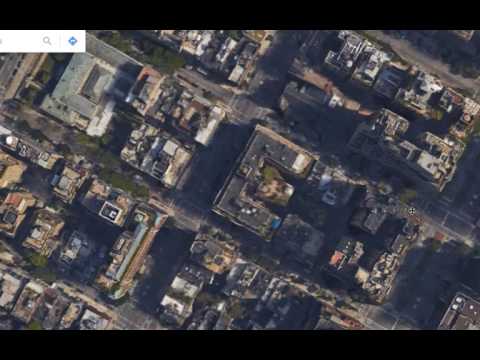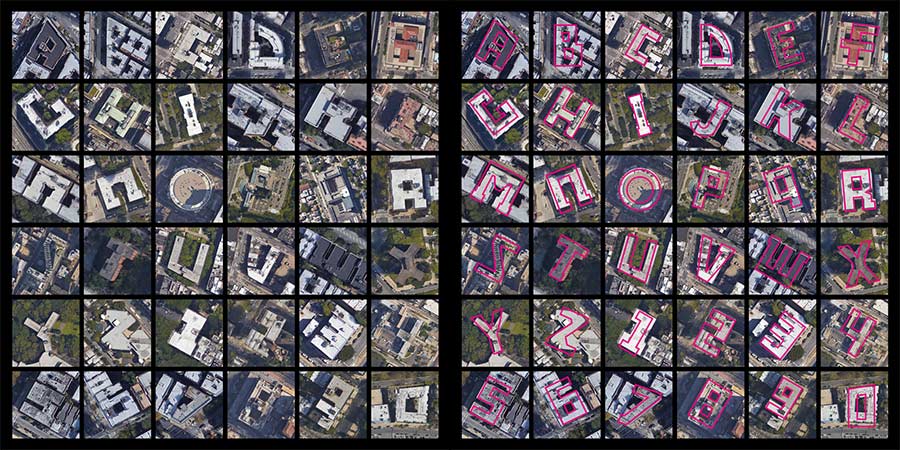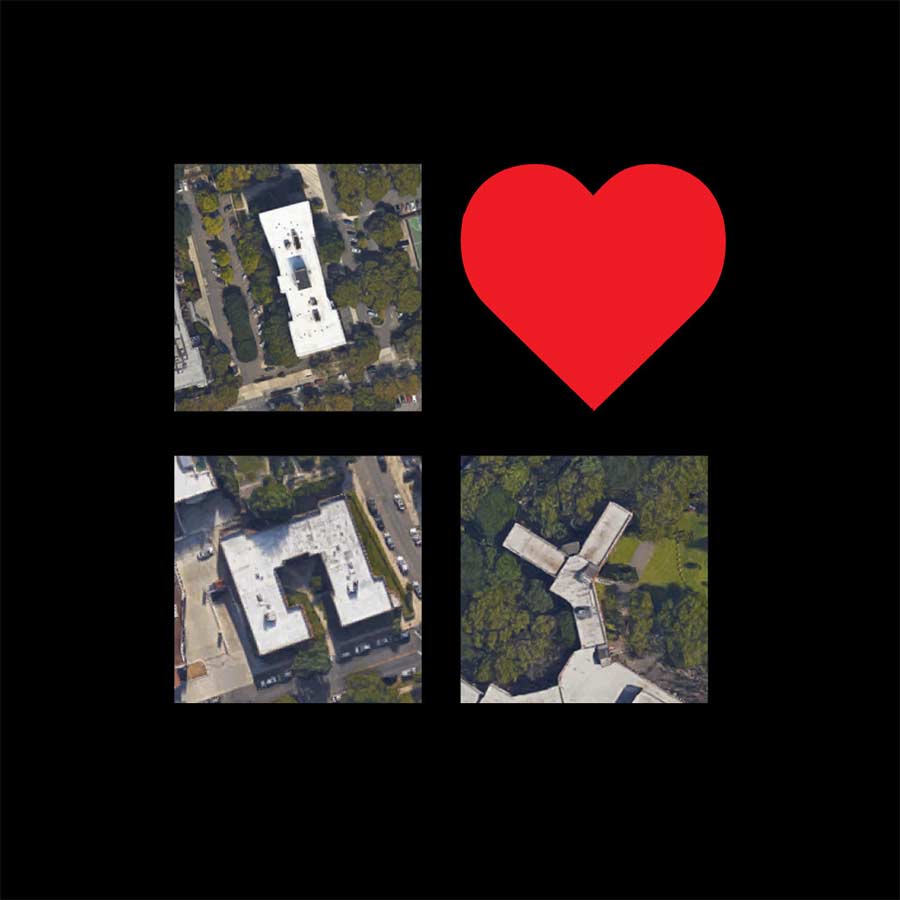
Capitals: Schriftart aus Hausformen New York Citys capitals-new-york-city-font_01
Sehr coole Idee: Die eigene Schriftart für eine Stadt, die aus Teilen der Stadt besteht. Nein, keine plumpen Sehenswürdigkeiten-Silhouetten, die effekthaschereiig in Buchstaben-ähnliche Formen gepresst wurden, sondern tatsächlich Abbilder von Stadtelementen. „Capitals“ hat sich in einer ersten Runde Luftaufnahmen von Gebäudeformen genommen, die schon von „Natur“ aus wie Buchstaben aussehen.
Hinter der Schriftart steckt aber nicht etwa eine Übersee-Agentur, sondern das Kreativen-Trio Invasione Creativa, Edoardo Santamato und Benedetto Papi aus Mailand. Anscheinend hat die eigene Stadt aber nicht die internationale Ausstrahlung oder 26-fache Luftansicht-Struktur, die es für eine Umsetzung benötigt.
„Here our new typo-graphic project based on the study of a particular class of font. Analyzing google maps, we realized that every city possesses its own font. Hidden in plain sight. A unique and special font linked directly to the territory, directly to the city, to the buildings. All you need is to take a look from the sky.“